Rico em detalhes
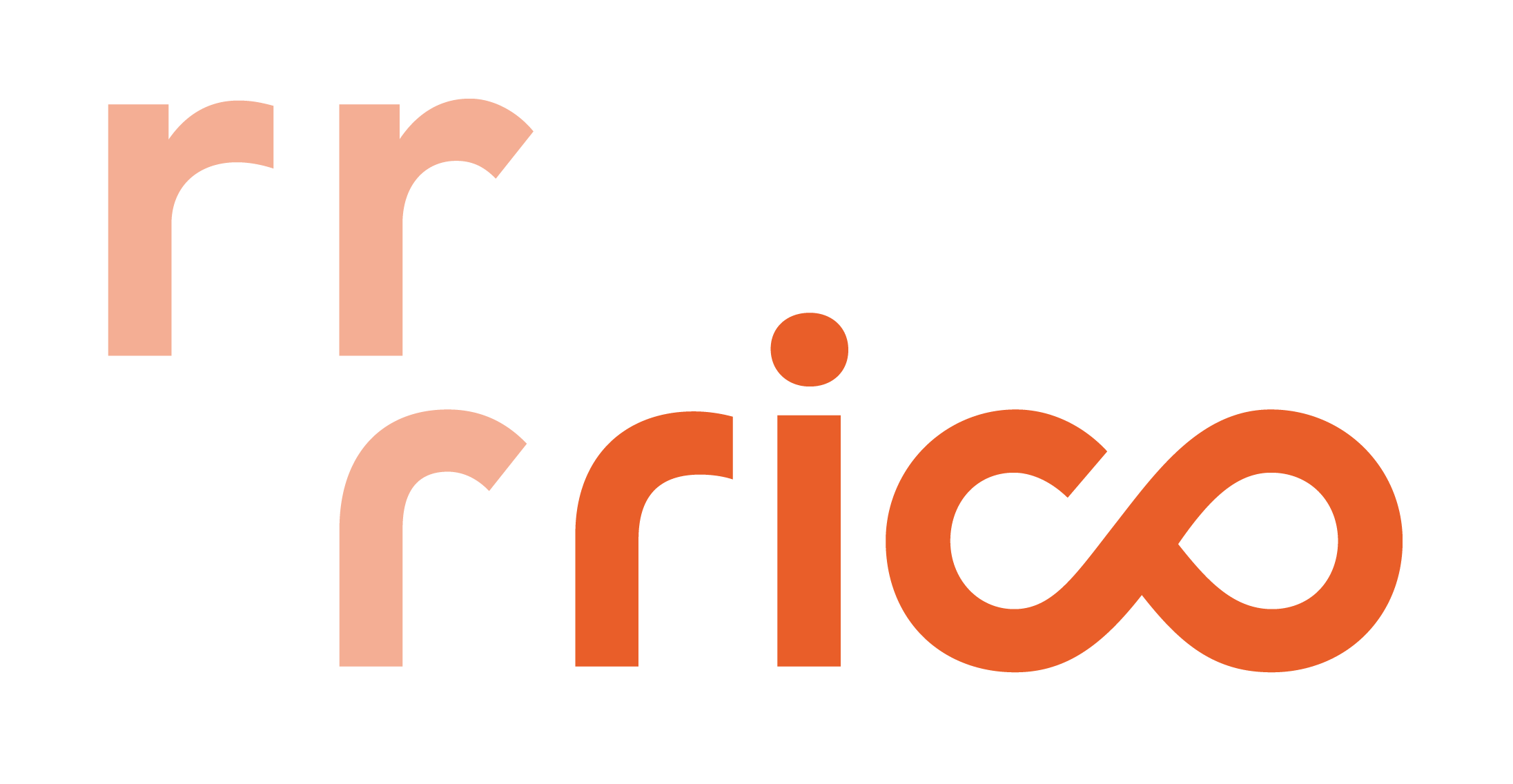
Da Vinci escreveu que são os detalhes que fazem a perfeição, e que a perfeição não é um detalhe. Quando a Tátil Design nos convidou para auxiliá-los no desenho do logotipo Rico, eles sabiam muito bem o que Da Vinci queria dizer.
Nós, type designers, temos uma vantagem em relação aos designers gráficos. Temos o privilégio (alguns dirão que é maldição) de trabalhar focados apenas em retas e curvas, preto e branco, todos os dias. Não existem camadas de elementos, cores, fotografia ou grafismos para nos preocupar; apenas o preto e o branco, de formas e contra-formas.
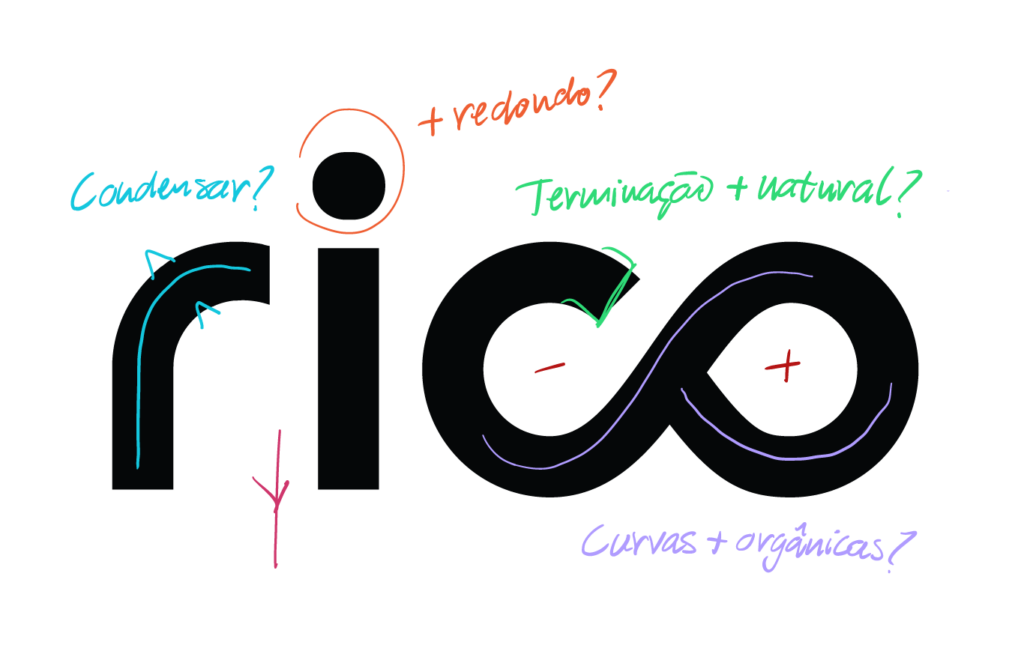
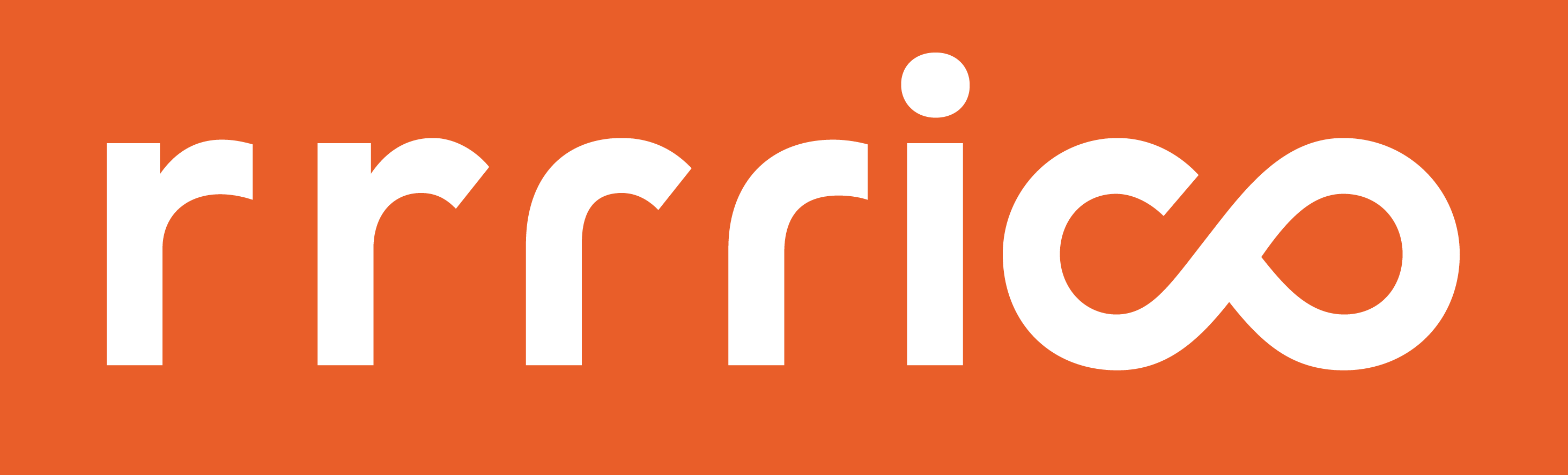
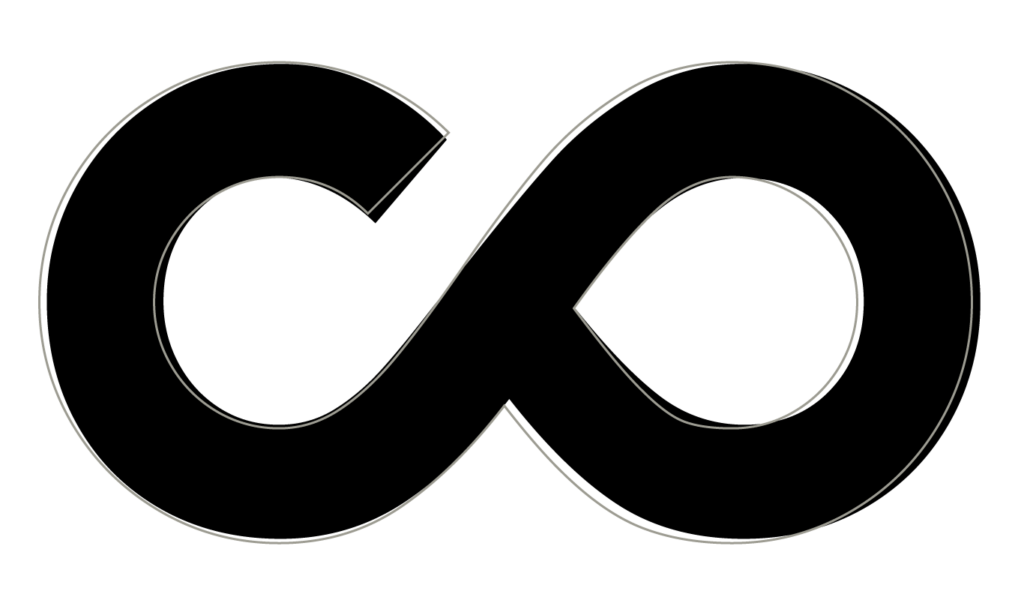
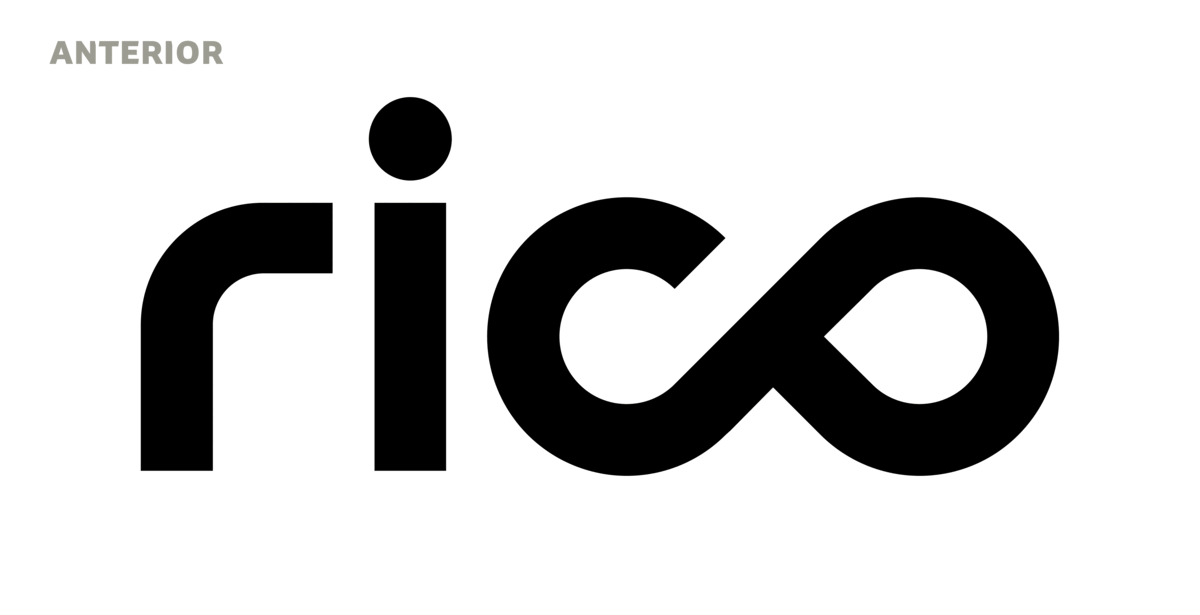
Nosso desafio foi explorar possibilidades que trouxessem maior fluidez, com curvas mais naturais. A ligatura “co” foi particularmente difícil. A abordagem geométrica resulta em formas mais rígidas. Compensações visuais foram feitas para alcançar um traço mais orgânico. Um novo ângulo da terminação no “c” trouxe mais equilíbrio entre os lados. Variações para a letra “r” também foram testadas; um exercício que só reforçou a harmonia da forma original. No final, ele recebeu apenas um truque: seu tamanho foi reduzido, já que sua parte superior dá a ilusão de ter maior altura.
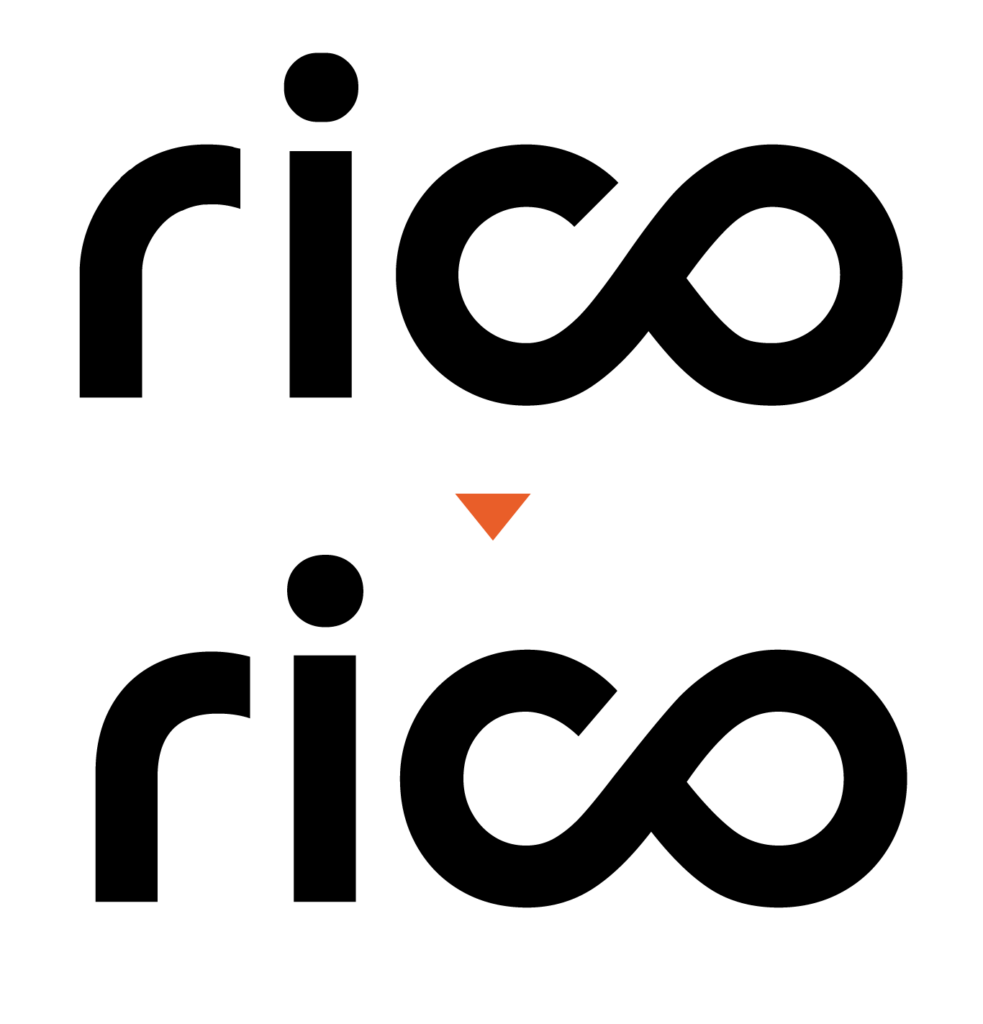
Um processo minucioso, mas visível até para quem não tem um relacionamento monogâmico com as formas básicas, como nós. Afinal, não estamos falando de detalhes.